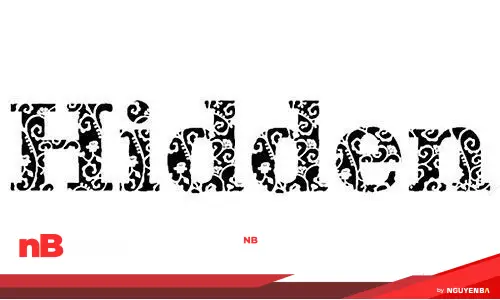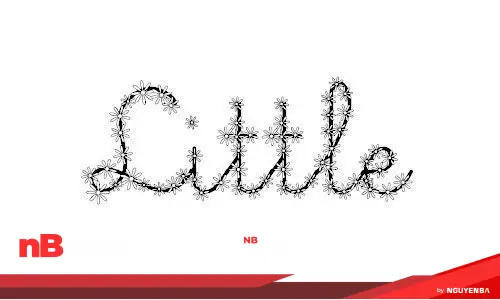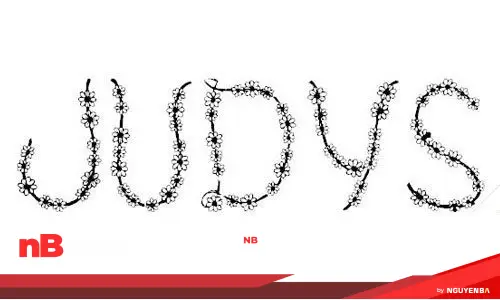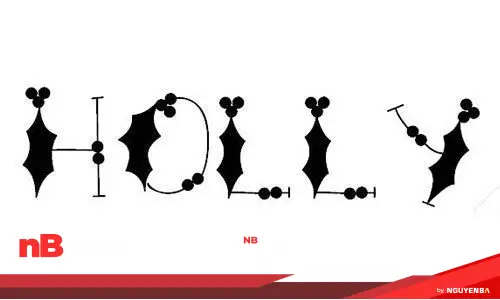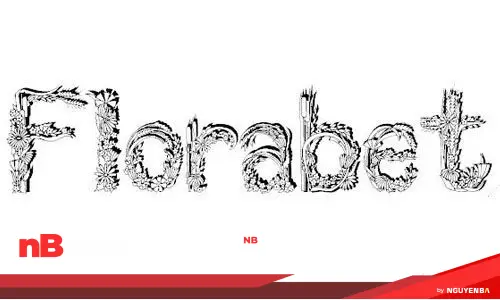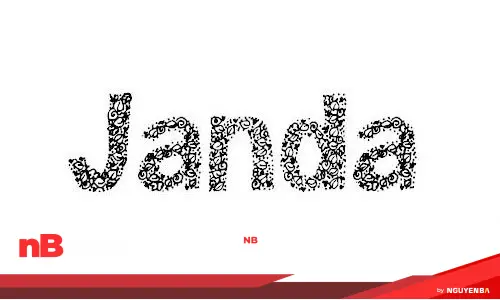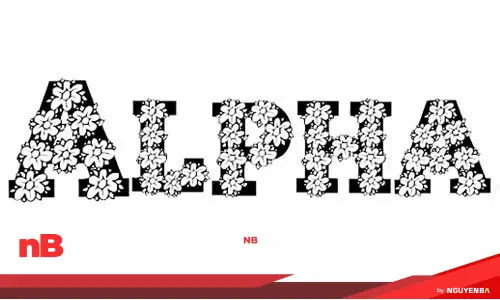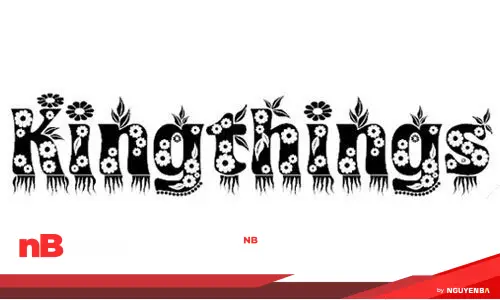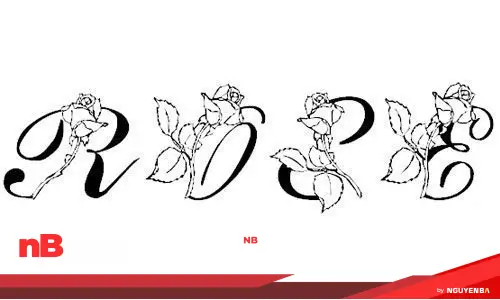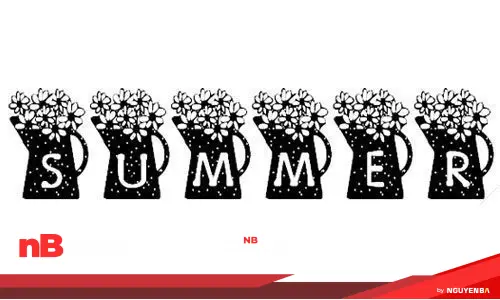
Gợi ý chọn font theo phong cách thiết kế
30 font trong bộ sưu tập có thể chia thành 4 nhóm phong cách. Tùy mục đích thiết kế mà bạn chọn nhóm phù hợp:
1. Nhóm lãng mạn, nữ tính
Gồm các font như Flowers, Little Daisy, Florabet, Judy’s Garland, LMS Rose, LMS Corinne’s Roses, MTF Wildflower, Bloesem. Đặc điểm là nét chữ mềm, hoa nhỏ li ti điểm xuyết tinh tế. Rất hợp làm thiệp cưới, thiệp cảm ơn, logo spa hoặc shop hoa — những nơi cần sự nhẹ nhàng, tinh tế.
2. Nhóm vui nhộn, đáng yêu
Gồm FLOWERcomic, FlowerSketches, Summer’s Country, Coffee Pots KR, LMS Hippy Chick, Flower Frame Flower, Blomster. Nét chữ tròn trịa, ngộ nghĩnh, hoa lá to bản và sinh động. Dùng cho thiệp sinh nhật, poster lớp học, ảnh hoạt hình hoặc thiết kế cho bé sẽ rất “ăn” hình.
3. Nhóm cổ điển, sang trọng
Gồm Floral Caps Nouveau, Kingthings Annex, LMS Calla Lily, Alpha Flowers, Janda Rosalie. Phong cách art-nouveau hoặc serif cổ điển kết hợp họa tiết hoa trang nhã. Phù hợp với bìa sách, menu nhà hàng, thiệp mời sự kiện trang trọng hoặc branding cho thương hiệu cao cấp.
4. Nhóm đơn giản, dễ đọc
Gồm Sophie Scholl, PlantsLetters, Flower Flora1, Holly & Berrie, JI Hidden Vines, Shower Flower, LMS Daisy Days KR, Filled With Flowers. Hoa lá được tiết chế, chữ vẫn rõ ràng ở nhiều cỡ khác nhau. Đây là nhóm an toàn nhất nếu bạn cần vừa đẹp vừa đảm bảo người xem đọc được nội dung — ví dụ tiêu đề bài viết, quote truyền cảm hứng, banner quảng cáo.
Mẹo nhỏ: trong một thiết kế, chỉ nên dùng tối đa 2 font trang trí. Một font hoa lá làm tiêu đề + một font đơn giản làm nội dung phụ là công thức an toàn và đẹp nhất.